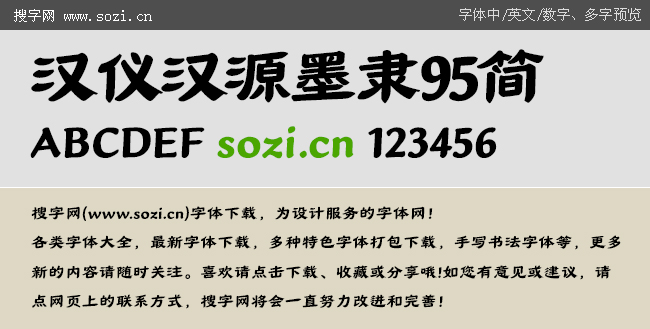
漢儀漢源墨隸95簡
搜字網(wǎng)給大家提供一款漢儀漢源墨隸95簡中文字體下載,漢儀漢源墨隸以現(xiàn)代設(shè)計(jì)手法重新演繹古老的帛書字體,樸素自然、古雅生動,氣質(zhì)簡約明快。書體介乎于篆隸之間,扁平取勢,略微向上傾斜,結(jié)構(gòu)緊密,規(guī)整之中流露放恣之色。給人以含蘊(yùn)圓厚之感;細(xì)款飄逸靈動,線條輕盈而不失纖韌。適用于畫冊設(shè)計(jì)、海報(bào)設(shè)計(jì)、包裝設(shè)計(jì)等場合使用。(本字體為個(gè)人非商用版,如需要商用請聯(lián)系漢儀公司購買版權(quán))